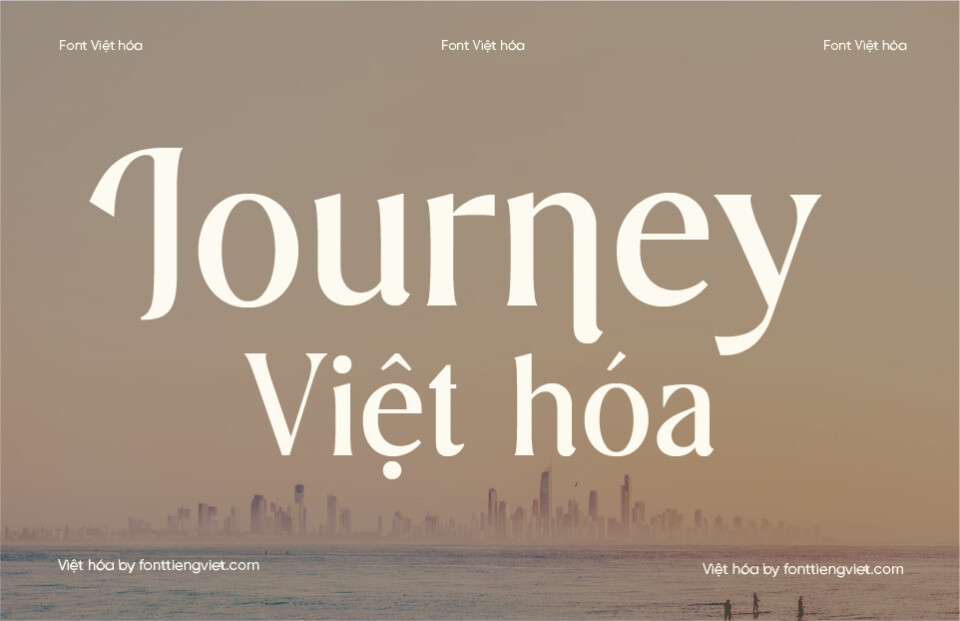
Trong thế giới thiết kế đồ họa hiện đại, việc lựa chọn một bộ Font Chữ phù hợp đóng vai trò quan trọng trong việc truyền tải cảm xúc của tác phẩm. Font Việt hóa 1FTV VIP SS Journey nổi lên như một lựa chọn hàng đầu cho các nhà thiết kế yêu thích phong cách tối giản nhưng không kém phần sang trọng. Đây là bộ font được tinh chỉnh kỹ lưỡng về dấu tiếng Việt, giúp người dùng dễ dàng ứng dụng vào các dự án từ học tập đến công việc chuyên nghiệp mà không lo lỗi hiển thị.
Đặc điểm nổi bật của Font Việt hóa 1FTV VIP SS Journey
Phong cách thiết kế hiện đại
Bộ font này sở hữu những đường nét thanh mảnh, dứt khoát, mang lại cảm giác phóng khoáng và tự do đúng như tên gọi Journey. Sự kết hợp giữa các nét cong mềm mại và cấu trúc hình học chuẩn mực giúp 1FTV VIP SS Journey trở nên cực kỳ linh hoạt. Bạn có thể sử dụng font chữ này cho các tiêu đề sách, bìa tạp chí hoặc các biểu ngữ sự kiện tại trường học một cách hiệu quả.
Khả năng tương thích và Việt hóa hoàn chỉnh
Điểm mạnh nhất của Font Việt hóa 1FTV VIP SS Journey chính là bộ dấu tiếng Việt được thiết kế cân đối. Các ký tự như đ, ê, ơ hay các dấu thanh đều được đặt ở vị trí hợp lý, đảm bảo tính thẩm mỹ cao nhất. Điều này giúp các bạn học sinh và sinh viên dễ dàng tạo ra những bài thuyết trình ấn tượng hoặc các ấn phẩm truyền thông chuyên nghiệp mà không gặp bất kỳ rào cản kỹ thuật nào.
Ứng dụng thực tế và cách sử dụng hiệu quả
Với vẻ ngoài tinh tế, bộ font này thường được ưu tiên dùng trong các thiết kế thương hiệu, thiệp mời cao cấp hoặc làm layout cho website. Khi sử dụng, bạn nên kết hợp với các tông màu trung tính để làm nổi bật sự sang trọng của phông chữ. Hy vọng rằng bộ Font Miễn Phí, Font Việt Hóa, Font Việt hóa 1FTV VIP SS Journey sẽ là nguồn cảm hứng mới giúp bạn tạo nên những sản phẩm sáng tạo độc đáo và mang đậm dấu ấn cá nhân trong tương lai.